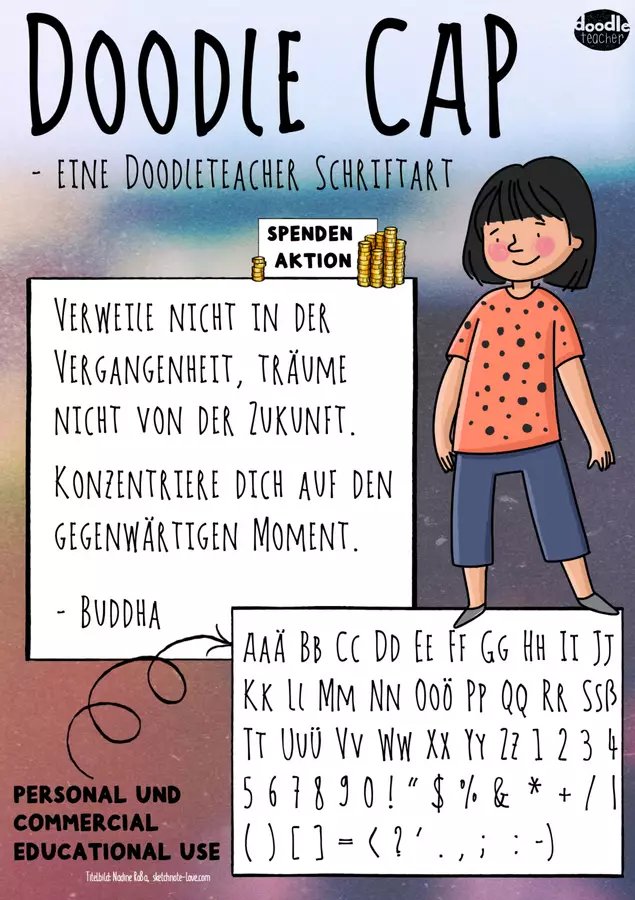
Eine sehr schöne Schrift die nur Großbuchstaben besteht (es gibt zusätzlich aber kleinere Großbuchstaben). Sie ähnelt in ihren Grundzügen der beliebten Amatic Schriftart ist aber  etwas freier und doodeliger angelegt. Gibt es auch im PAKET!
Doodle Cap - Font / Schriftart